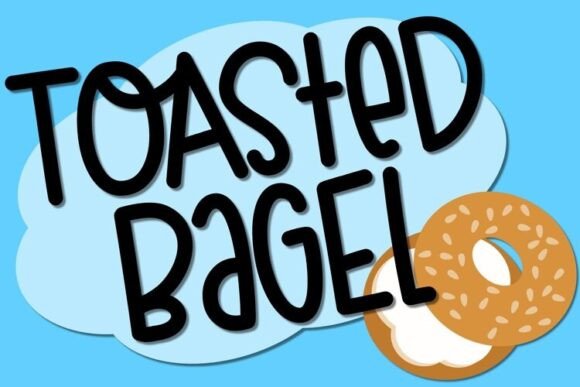
Toasted Bagel
Trouver les bons éléments de conception peut être un défi, mais Toasted Bagel propose une collection exceptionnelle qui rehausse instantanément votre travail.